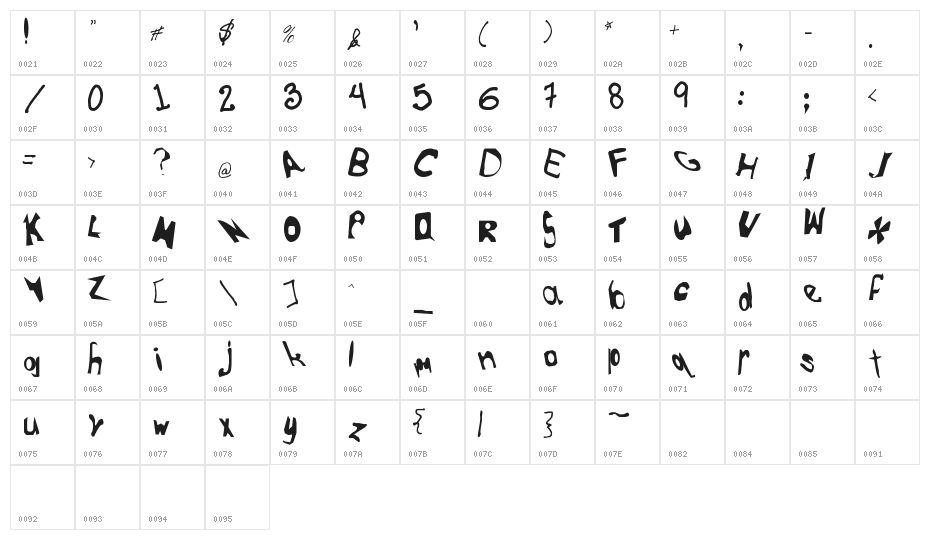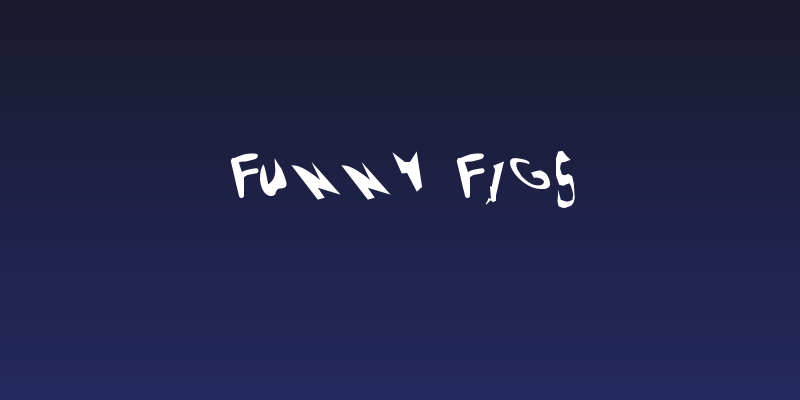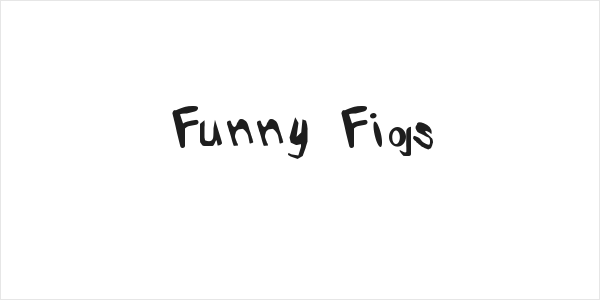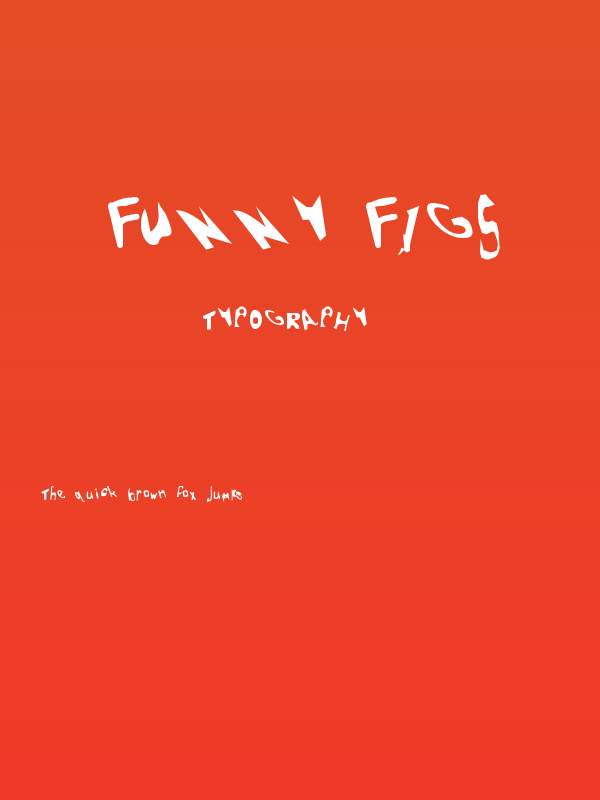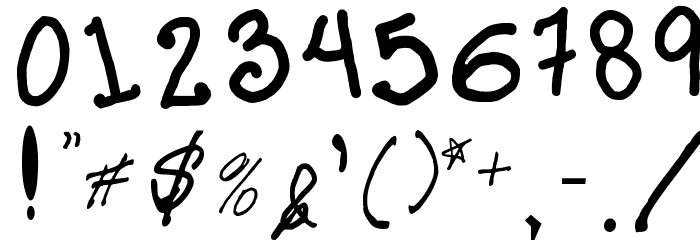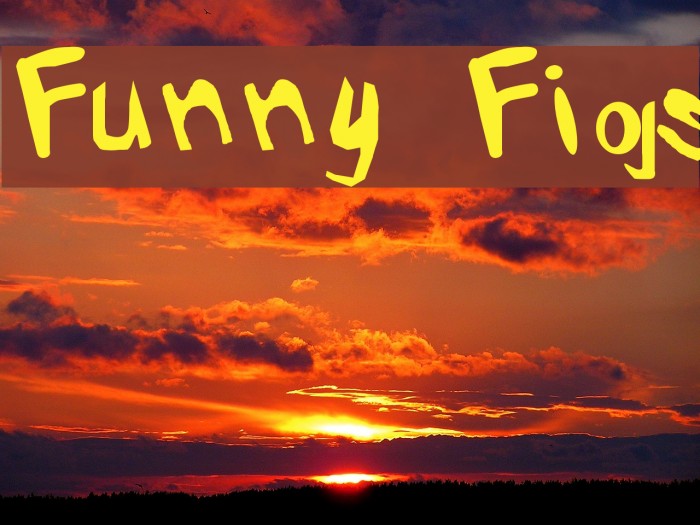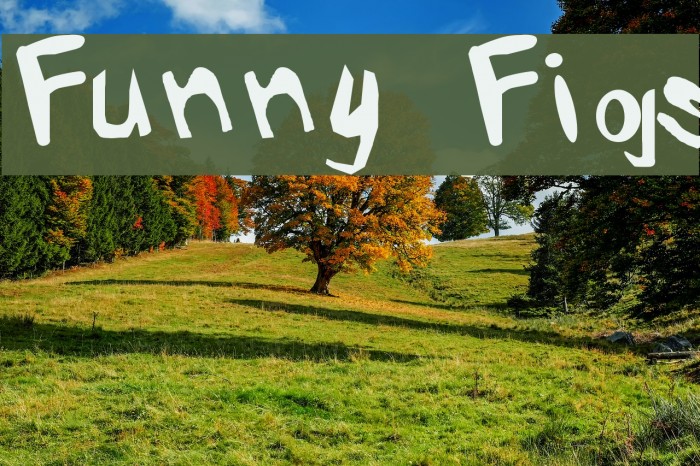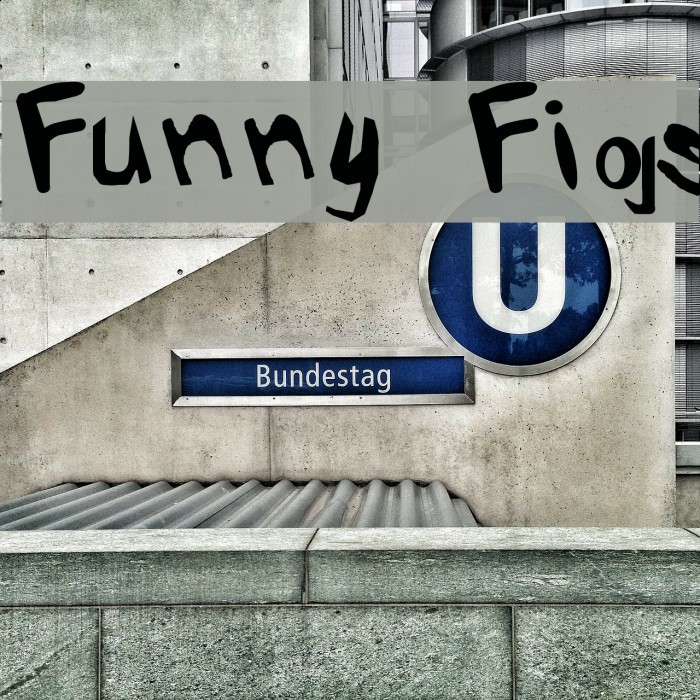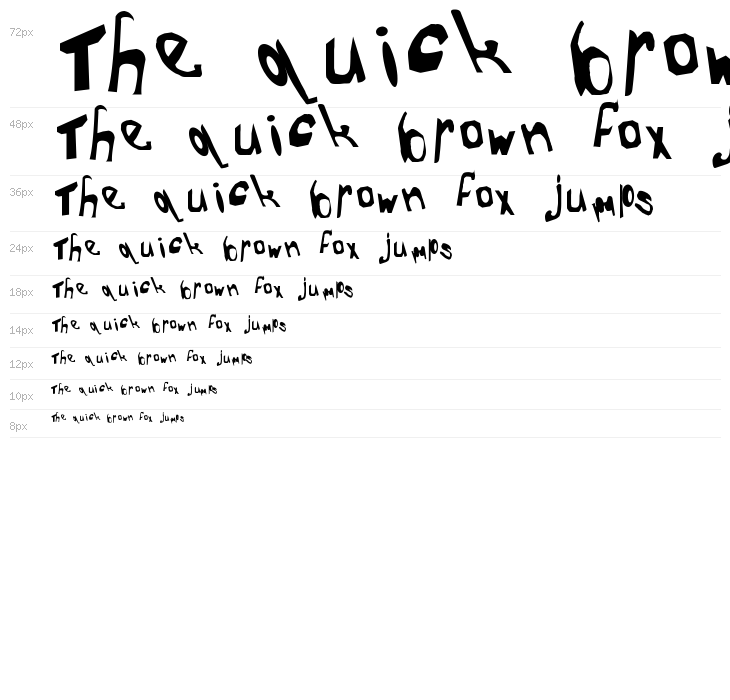
Funny Figs Font
| Estilo general | Playful, Whimsical |
| Caso de uso | Headlines, Posters, Creative Branding |
| Proyectos propuestos | Ideal for children's books, comic strips, playful branding, and creative posters. |